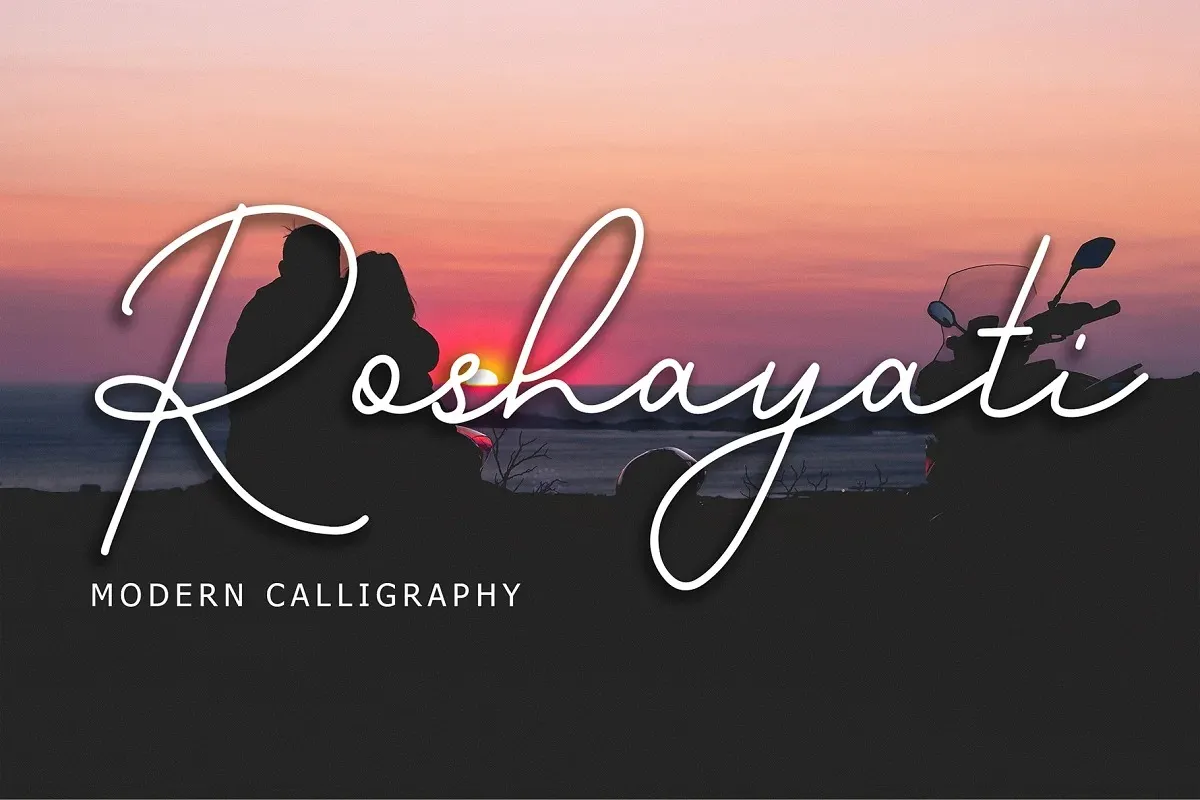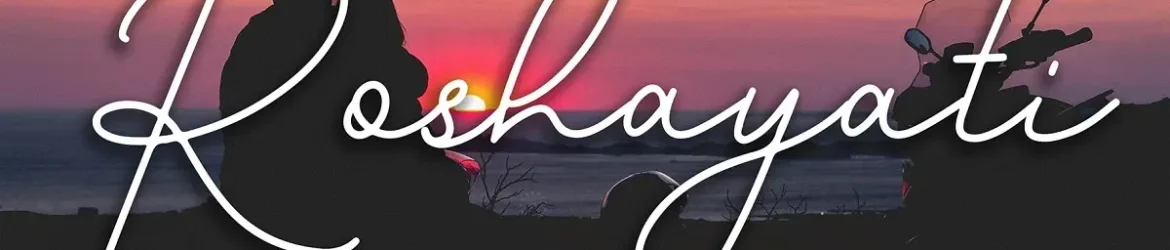
A Roshayati Font é uma elegante fonte script que captura a essência da tipografia vintage para ajudar você a criar designs com estilo inovador e sofisticado. Esta fonte, criada pelo designer Formatika Studio na plataforma de design 99designs, oferece um equilíbrio perfeito entre curvas suaves e formas geométricas, o que a torna uma escolha ideal para aplicações em moda, editorial e design gráfico. Suas linhas leves e definidas permitem criar designs profissionais com um toque elegante, especialmente adequados para marcas de marca, criação de logotipos, embalagens de produtos, identidades digitais, cartazes e outras iniciativas visuais. A Roshayati é uma escolha perfeita para qualquer projeto que exija uma combinação única e sofisticada entre estética e funcionalidade.